10款超级有设计感的英文运动字体
这组顶尖设计师私藏的英文运动字体,是运动精神的视觉化体现! 它们极具速度、力量、激情和未来科技的视觉化效果。无论您正在设计体育赛事海报、健身App界面、电竞品牌Logo,还是户外运动装备宣传页,这些字体都能提供无可比拟的视觉冲击力和专业的动感氛围。
Quadrophonic
一款现代、时尚且极具特色的精简无衬线字体,适用电影海报、电影标题、海报、标题、封面、杂志、网站、时尚和街头服饰、引言、图像文字等。
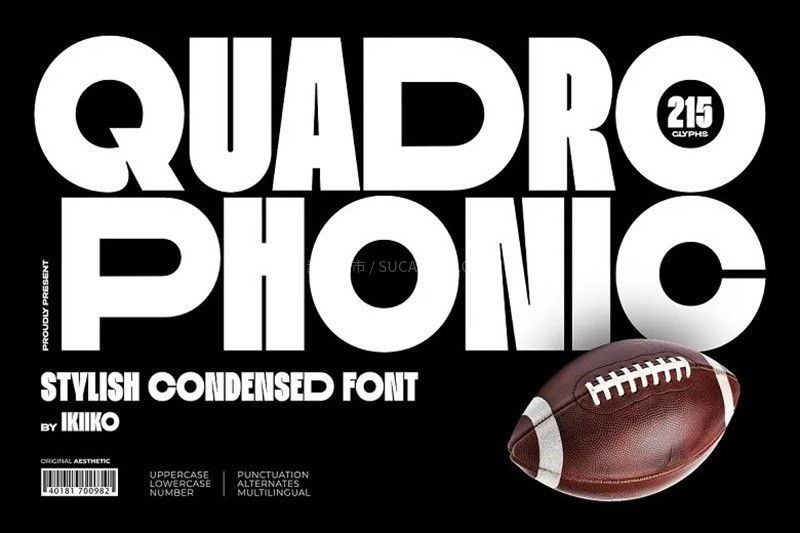
ORVADO
一款专为运动、健身和动感品牌打造的现代展示字体。凭借其大胆的结构、锐利的线条和强大的视觉冲击力,ORVADO 为每一个设计注入活力与力量。
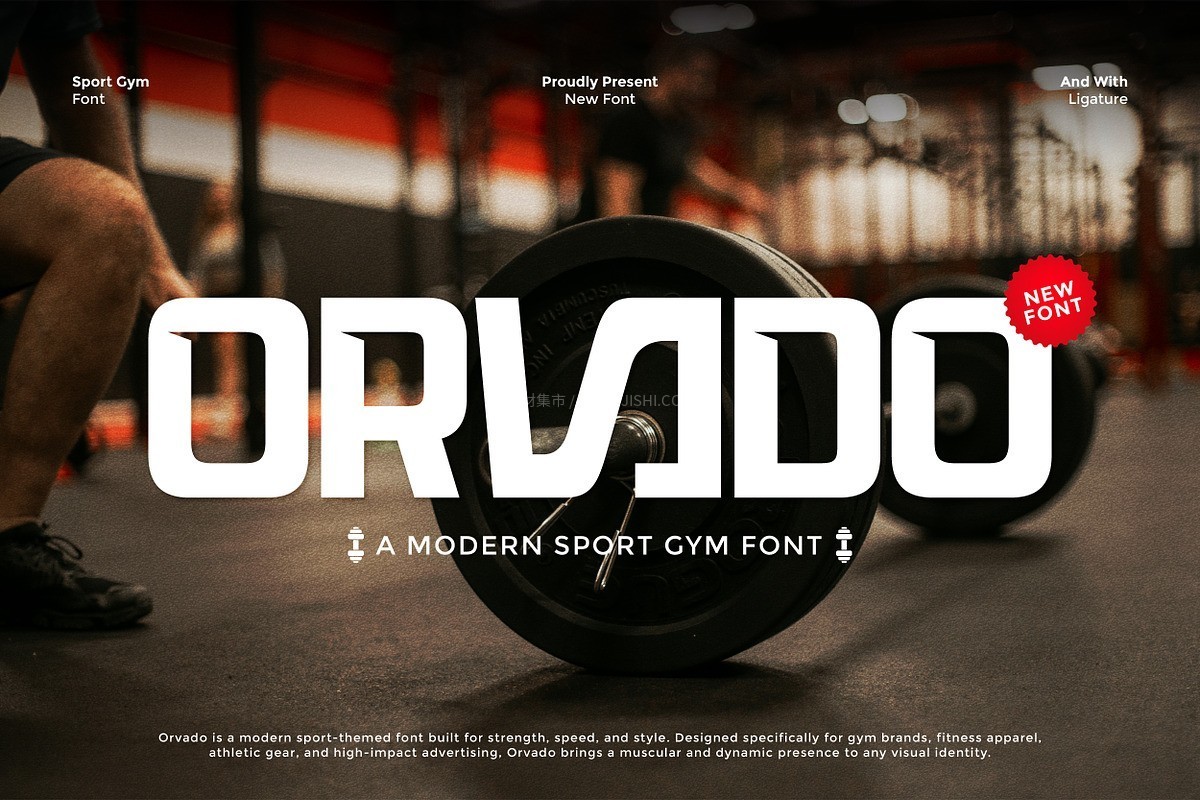
JUMPSHOT
一款专为体现速度、力量和动感而设计的运动风格字体。它以其大胆的笔触、强烈的几何曲线和前卫的结构,完美捕捉了竞技体育的激动人心的节奏和爆发力。
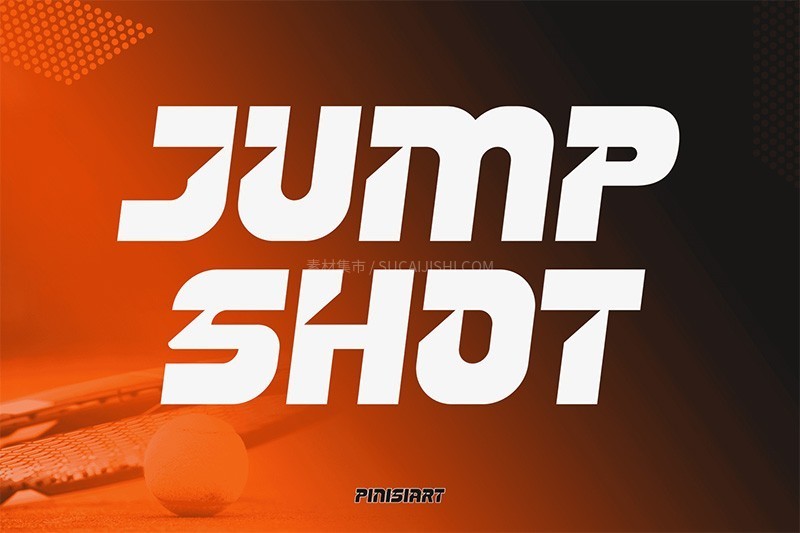
Shooket
一款极具冲击力的运动字体。拥有动感的角度和澎湃的运动能量,让您的设计看起来更快、更强、更具竞争力。Shooket 完美适用于体育品牌、游戏标识和醒目的标题,每个字形都展现出强烈的视觉冲击力和专业的设计感。
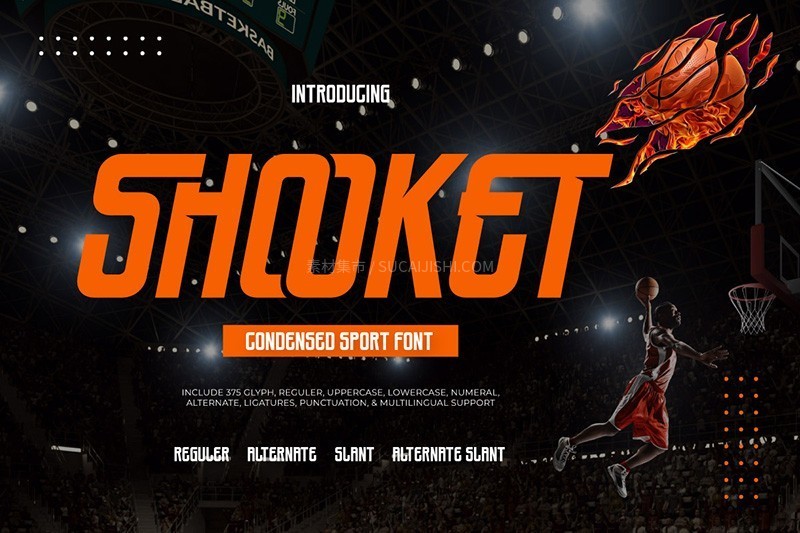
Fareno
一款现代而充满未来感的字体,适用于各种品牌和标志设计。这款现代而充满未来感的无衬线字体拥有优美的笔触。它适用于邀请函设计、酷炫的标志、电影片名、名片、书籍标题、品牌名称以及其他各种设计。
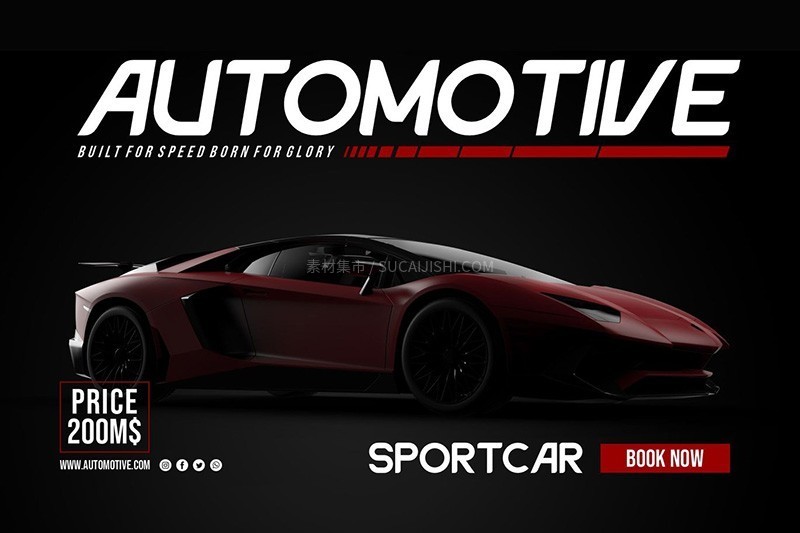
SPARTA
一款未来科技运动字体,专为标志、电影片名、动作海报、比赛设计等打造,非常适合为您的运动、科技、动作和格斗主题作品增添风格和标题概述。
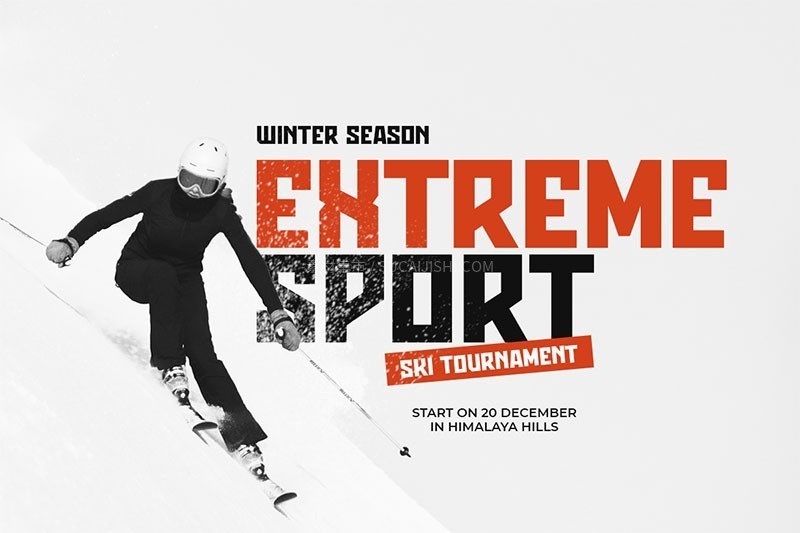
Roxbe
一款现代字体,其设计灵感源自运动和未来主义视觉设计。Roxbe 拥有强劲而独特的字形,能够让您的设计项目更具吸引力,脱颖而出。Roxbe 是一款功能齐全的字体,包含替代字形、连字,并且已支持多种语言字符。
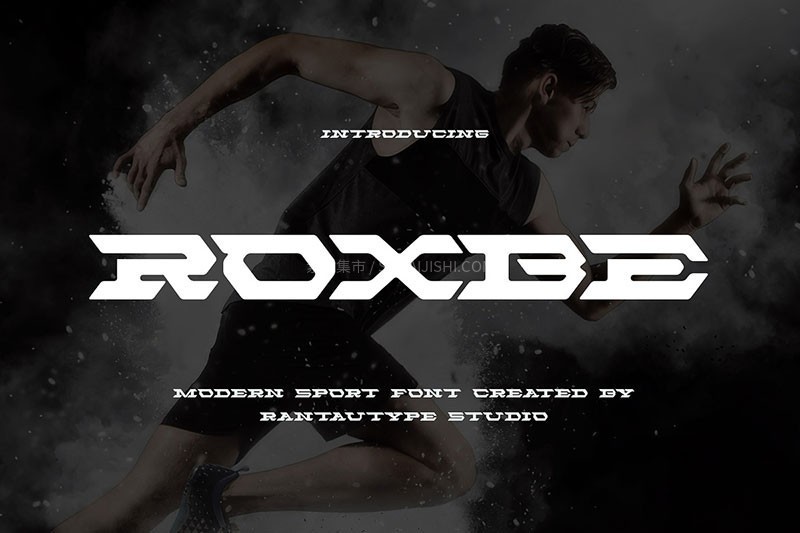
Turnan
一款活力和动感、充满未来感的运动科技字体,Turnan 将为您的品牌带来高科技感。 它锐利的棱角、几何结构和科技感十足的外观使其成为运动服装、汽车品牌、游戏、无人机技术和创新主题视觉效果的理想选择。 Turnan 包含大写字母、数字和各种标点符号,以满足您的创意布局需求。
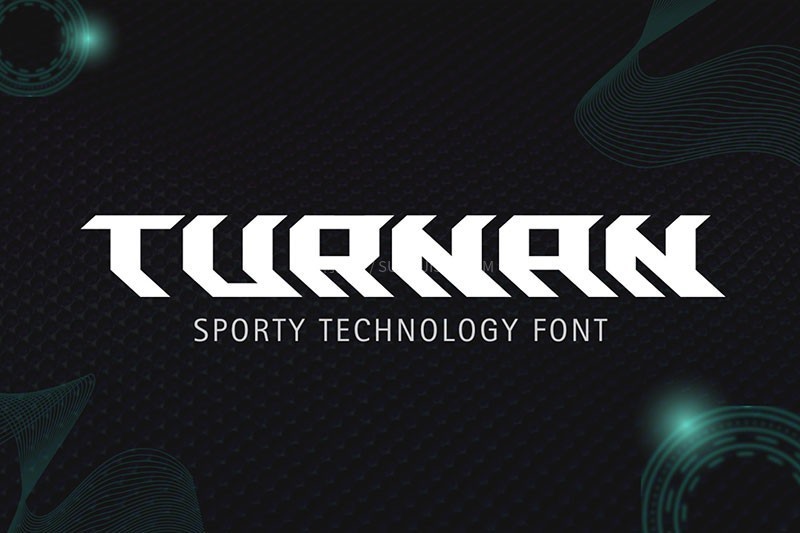
Jegasup
一款兼具力量感与专业度的展示字体,设计醒目,能在第一时间抓住受众目光。其清晰的结构和大胆的造型使其在标志设计、体育品牌、海报标题、电竞宣传等高冲击力的应用场景中表现卓越,是打造高辨识度品牌视觉形象的理想选择。
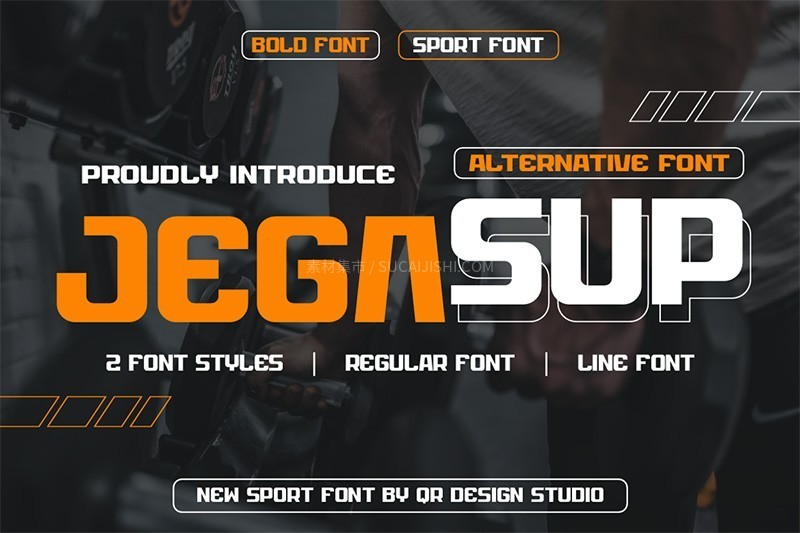
GearUp
这款现代优雅的无衬线字体家族,以其专业而清晰的结构,完美契合企业品牌和运动主题等广泛的项目需求。轻松融入您的创意理念,让您的设计作品在视觉上脱颖而出,彰显专业与时尚。